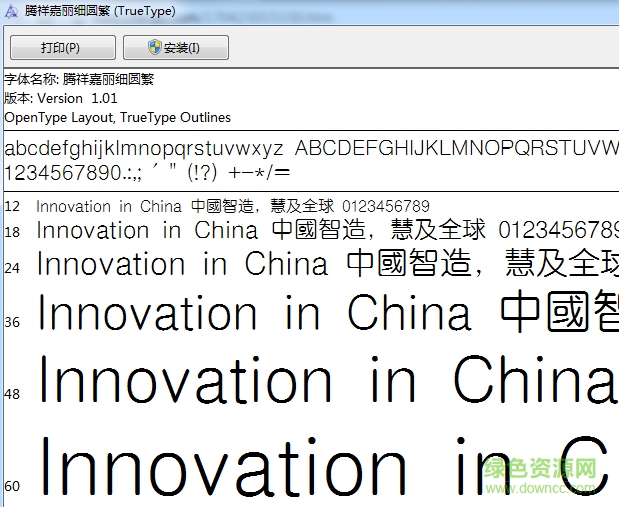
軟件介紹 軟件標簽: 其他字體 字體 騰祥嘉麗細圓繁字體是一款超好用的中文個性字體,字體線條清晰,能夠清楚的表達出你想要的效果,有喜歡這款字體的朋友可以來綠色資源網(wǎng)免費下載使用!騰祥嘉麗細圓繁字體安裝方法方法一:控制面板/字體/文件/安裝新字體;方法二:直接將字體復制到C:\WINDOWS\Fonts。方法三:針對win7系統(tǒng),用戶只需選中字體右鍵安裝即可。注意事項本站所有字體資源僅供個人學習與參考,如需商業(yè)使用請到相關官網(wǎng)授權。小編測評騰祥嘉麗細圓繁字體是一款極具個性的字體,該字體十分飄逸,彰顯了自己的個性,有喜歡的朋友可以來綠色資源網(wǎng)下載使用! 軟件截圖 上一張下一張(1 / 1) 安裝詳細截圖 猜你喜歡 騰祥字體 騰祥字體 騰祥字體(Tensentype)是由騰祥公司推出的一系列字體合集,開發(fā)推出了多款特色字體,如:騰祥嘉麗中黑簡、騰祥金磚黑簡、騰祥潮黑等,每款字體都很有特點,獨具個性,深受廣大朋友們的喜愛。 查看更多>> 騰祥豆豆體簡繁 8.78M/中文/5.0/v1.0 pd端下載 騰祥泡泡體ttf 5.89M/中文/5.0/下載 tensentype chaoheij字體 1.34M/中文/5.0/下載 tensentype xiangsif 2.44M/中文/5.0/下載 tensentype jinzhuanheij 2.44M/中文/3.3/下載 騰祥匆匆體繁 4.98M/中文/5.0/下載 其他版本下載 標題 大小 更新日期 下載 下載地址 電腦版 騰祥嘉麗細圓繁體 點擊報錯 軟件無法下載或下載后無法使用,請點擊報錯,謝謝! 關閉報錯反饋 請描述您所遇到的錯誤,我們將盡快予以修正,謝謝! *必填項,請輸入內(nèi)容 本類最新 dreamweaver字體庫 首爾南山體字體 v1.06 官方版 潮字社風云簡ttf 潮字社凌渡鯤鵬簡體字體 潮字社曾玉波手書簡字體 微博慧心字體 相關文章 Photoshop字體安裝使用方法和技巧 如何解決“無法新增字體”問題 Win 7系統(tǒng)安裝字體方法 網(wǎng)頁字體大小設置方法 怎么改網(wǎng)頁字體大小 在Linux系統(tǒng)中安裝字體的幾種方法 windows7字體顯示問題:打開某些程序的時候顯示的是亂碼 用戶評論 熱門評論 最新評論 發(fā)表評論 查看所有評論(0) 昵稱: 請不要評論無意義或臟話,我們所有評論會有人工審核. 字數(shù): 0/500 (您的評論需要經(jīng)過審核才能顯示)